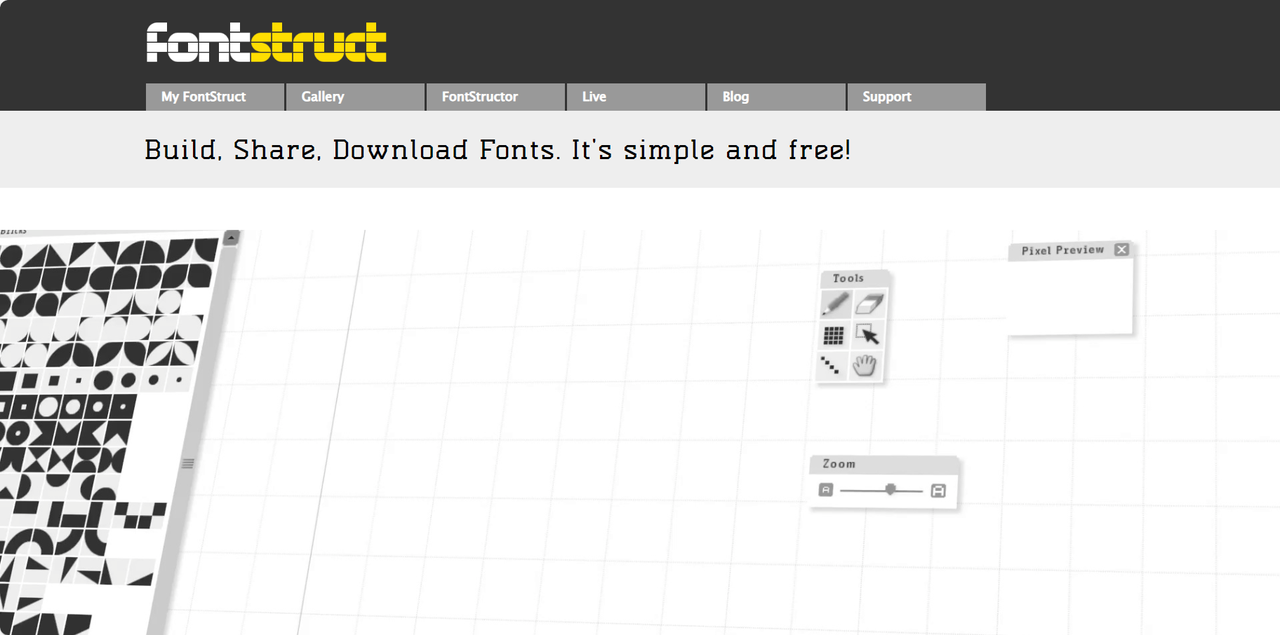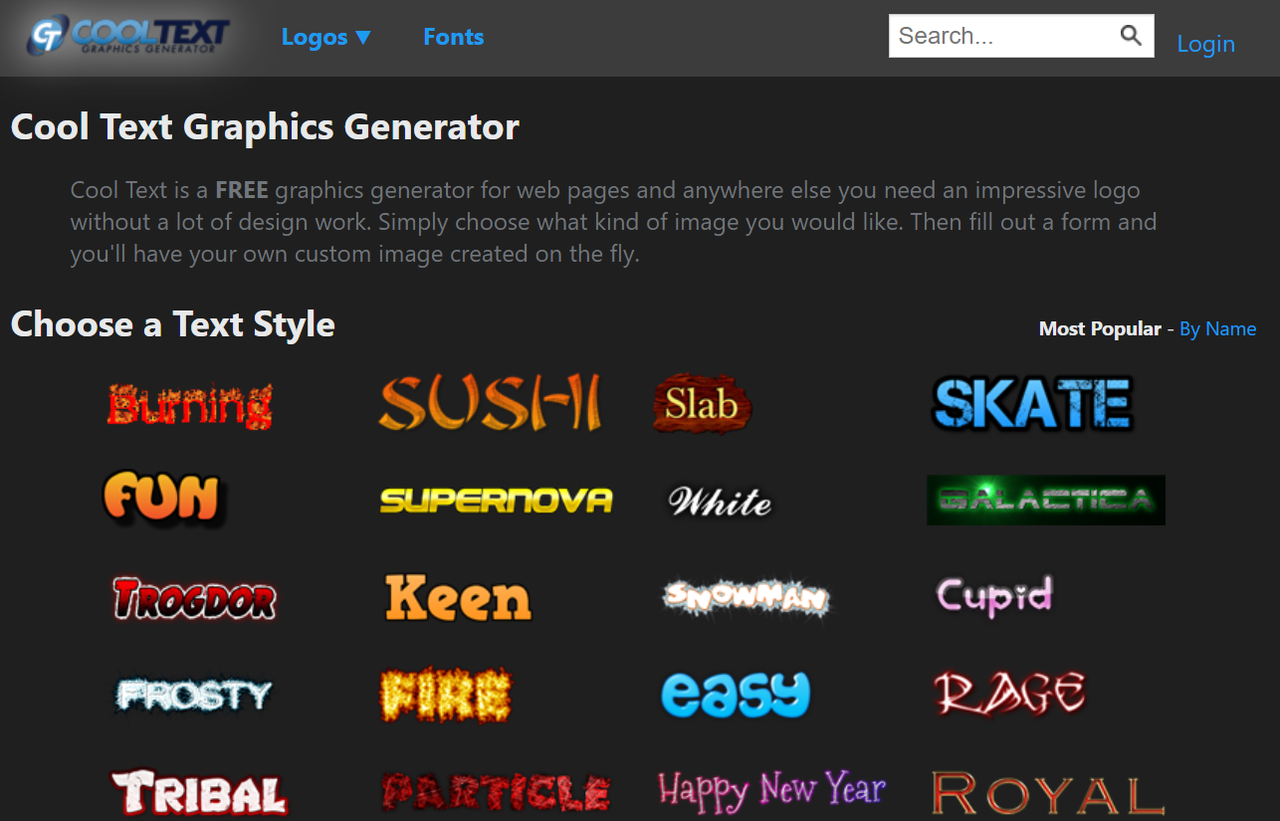
POP字体在线生成器,一键获得精美创意字体
POP 字体是专门为商业促销设计的醒目夸张且富有装饰性的手绘或数码字体,核心目的就是要在宣传场景中快速吸引注意力,激发顾客的购买欲。如果你想要做出活泼吸睛的文字但又不会自己画POP 字体,那么这些 POP 字体生成器真的会让你事半功倍!今天为大家整理了 6 款优质的 POP 字体在线生成器,国内国外的工具都包含在内,生成的字体免费无水印、适配多种风格,新手小白也可以一键打造专业级的精美 POP 字体,大幅提升设计效率,还能让你的设计更加光彩夺目!
一、字由
提到国内好用的 POP 字体生成器,字由绝对是很多设计师的首选工具,为创意字体设计带来了全新的体验。用户进入字由官网后,在顶部菜单栏点击【AI 工具】——【AI 字体】,即可进入 POP 字体创作页面,无需登录注册网站也能免费体验所有功能,对新手设计师很友好哦。然后大家可以根据自己的设计需求筛选 AI 字体模板,选中心仪模板后,点击做同款,在文本框输入自定义文本内容,即可一键获得同款 POP 字体。需要提醒的一点是,自定义文本字数最好和模板图片的字数相同,这样生成字体的效果会更好。下载 POP 字体时可以选择透明背景的 PNG 格式,后续直接将字体文件导入其他设计软件会非常方便,不会出现格式不兼容的问题。不管是新手还是老手,都能在几分钟内做出专业级的 POP 字体效果,是国内 POP 字体在线生成器中兼具实用性与创新性的优质选择。
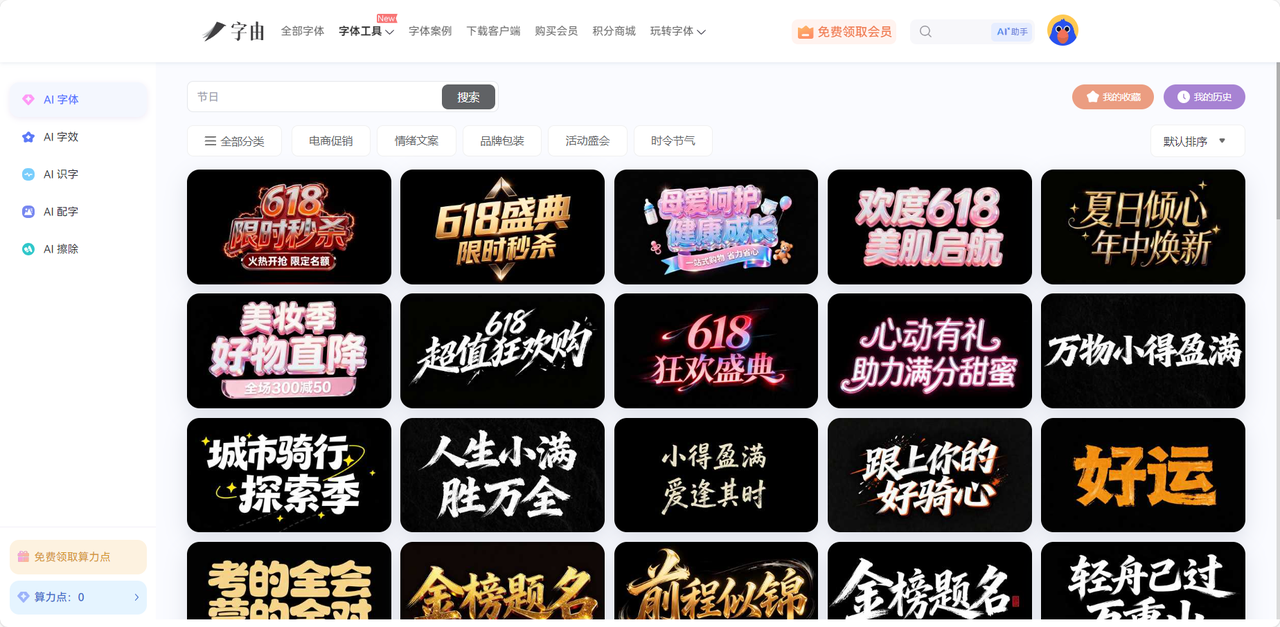
二、FontStruct
FontStruct 是凭借独特的模块化设计理念,逐渐成为了设计师们青睐的宝藏工具。用户主要是通过拼贴基础的几何形状,从零开始构建自己想要的 POP 字体,考验设计者的设计能力,同时也给大家提供了丰富的自由度。其实,FontStruct 的操作逻辑非常清晰,主页做测试形状素材库,中间是画布,右侧是参数调整面板,只需要选择自己满意的形状来拼接成字母笔画,轻微调整细节即可快速获得 POP 字体,非常适合追求个性化和的用户。生成后的字体支持下载为 TTF、OTF 等通用格式,便于后续导入其他设计软件中使用,或者也可以下载 PNG 格式的字体图片,用于快速排版。如果你对自己的设计能力没有自信,FontStruct 还提供了用户交流空间,你可以在这里下载其他设计师上传分享的POP字体模板并二次创作修改,无需自己手动制作字体,节省了大量的时间。
三、Cool Text
想必大家对于 Cool Text 也并不陌生,这是一款老牌的字体特效工具,而且操作零门槛、下载便捷、风格丰富多样。用户进入官网之后,只需要选择合适的字体特效,输入自己想要生成的文字内容,即可获得 POP 字体,这里内置的上百种模板涵盖了霓虹、复古、立体发光、浮雕、涂鸦等多种艺术风格,能满足各类设计场景。最关键的是,每个模板都支持自定义调整,用户可以自由修改字体颜色、描边、阴影或者添加文字效果,让你的 POP 字体更加绚丽多彩。个人觉得,用 Cool Text 生成的字体更适合用于电影标题、海报标题等视觉冲击力极强的场景里,会给你加很多分哦。虽然的它的自由度不如 FontStruct ,但是丰富的预设模板以及字体特效会保证 POP 字体的美观性以及实用性,也比较适合着急想要 POP 字体的用户,是国外设计工具中性价比较高的选择。
四、TextGiraffe
不同于上述几个 POP 字体在线生成器,TextGiraffe 是一款专门为社交媒体内容打造的字体生成工具,最大的优势就是可以适配不同平台的字体风格,可以一键生成适合 Instagram、TikTok 等外媒平台的创意 POP 字体,非常适合一些自媒体创作者拿来做短视频封面、社交媒体配图、文案等。由于这款工具的功能调性,它的界面设计也非常年轻化,用户可以在生成 POP 字体的基础上再去调整字体北京、装饰元素,还可以添加贴纸、小图标、emoji 呢,让字体更加符合社交平台的风格。就我个人的体验来讲,TextGiraffe 生成的字体会更加活泼吸睛、自带一些潮流网感,很容易吸引到年轻群体,所以如果你最近的设计面向的是青年一代,不妨来试试这个工具,会是一个不错的选择。
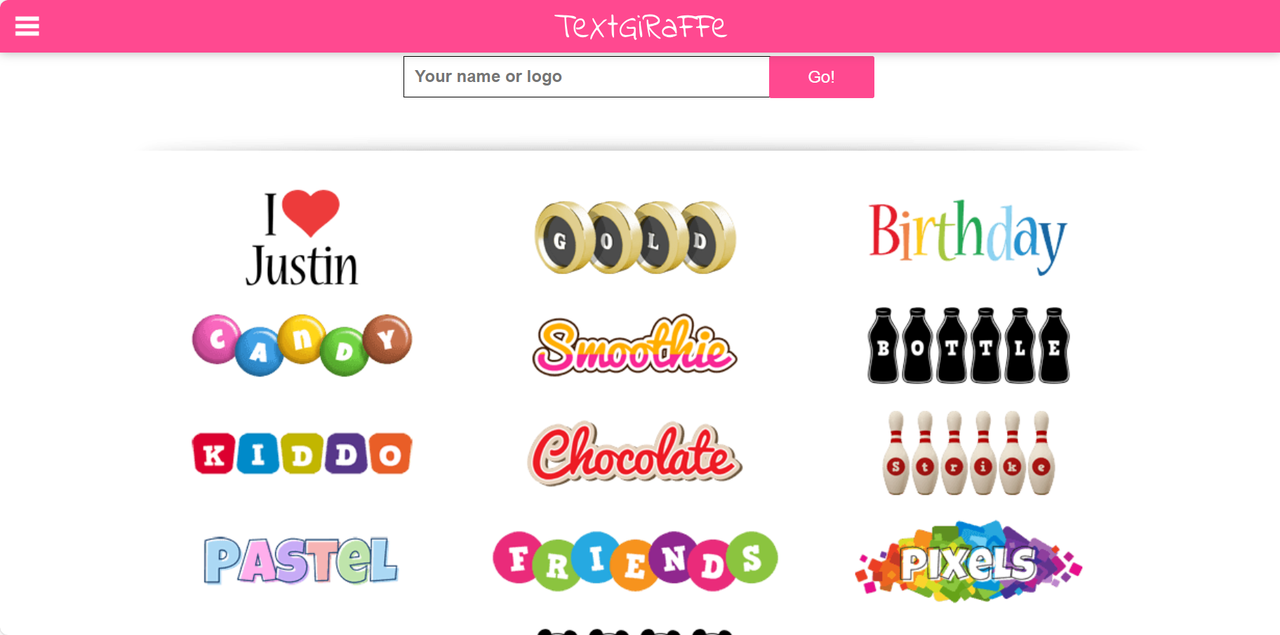
五、Font Meme
Font Meme 是国外非常知名的免费 POP 字体在线生成器,它还是一个不错的字体分享平台。值得一提的是,Font Meme 提供大量无版权限制的 POP 字体模板,不管是个人使用还是商业项目,用户可以免费生成并下载字体,完全无需担心版权问题。整体的 POP 字体生成流程和字由比较像,也是先选择模板,然后一键生成同款字体效果,不过它的页面是全英文,可能对国内的设计使用户来说不太友好。它的字体库非常丰富,用户可以按照场景、热度、风格筛选想要的字体,快速找到心仪的字体模板,生成后的字体不仅支持 PNG 格式下载,无水印、无压缩,画质清晰,也支持 TTF 格式,能直接导入设计软件中使用,商用也完全合规。而且你完全不用担心这些字体模板会过时,Font Meme 会经常新增热门风格的字体模板,帮助你了解当下的字体行业潮流,是个不可多得的字体在线生成器。
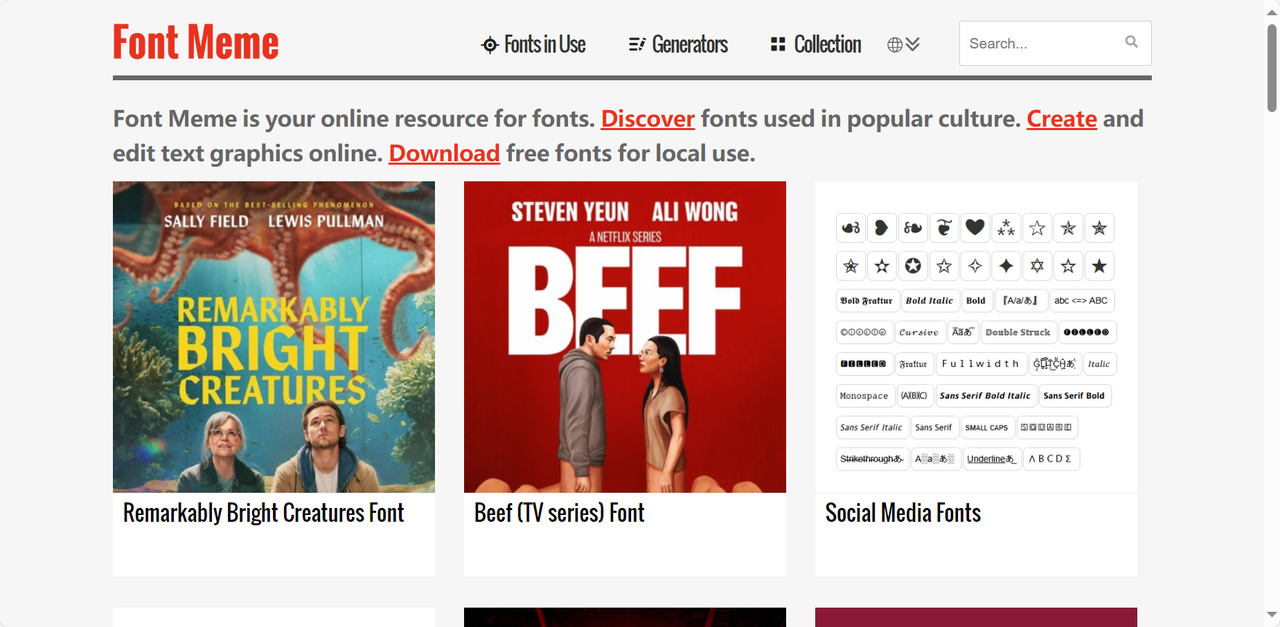
以上就是本次推荐的 5 款 POP 字体在线生成器,每个工具都有自己独特的优势,能适配日常中的不同场景的设计需求。有了这些工具的帮助,即使不会自己动手设计字体、对于很多设计软件也不太精通,这些通通都不是问题,你只需要按照不同工具的操作流程,一键就能生成吸睛的创意 POP 字体效果,大幅提升设计效率和作品的质感!赶快收藏这些工具,下次做宣传海报的时候,轻松打造一个夺人眼球的 POP 字体标题吧!